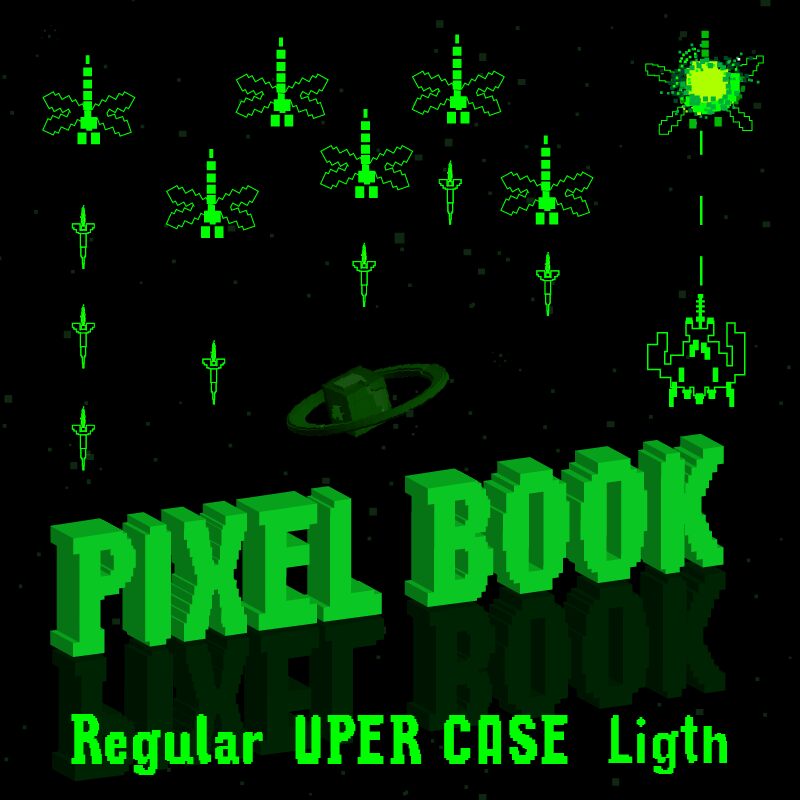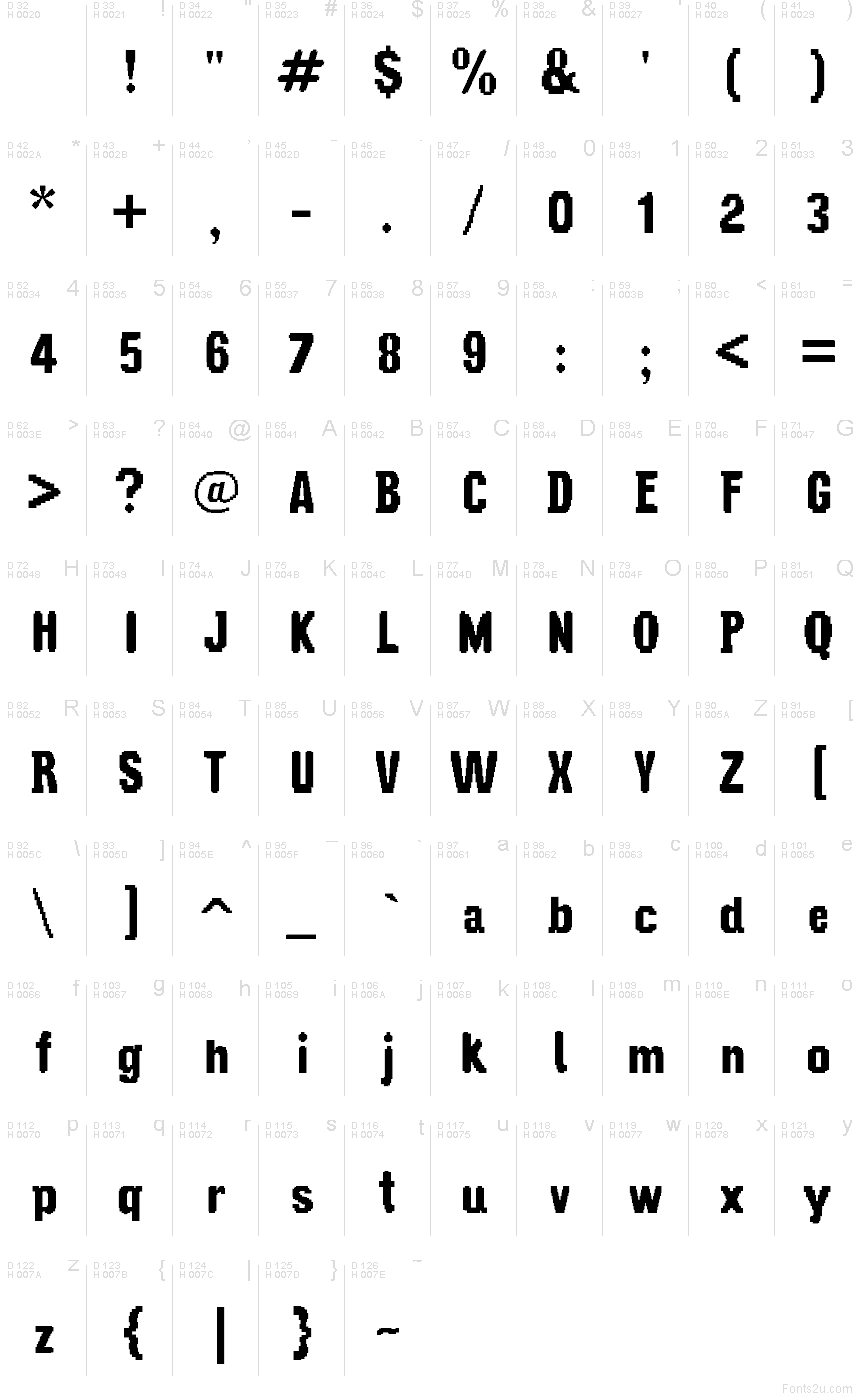
Pixel Book je bezplatný pixelový font od Galdino Otten. Písmena odkazují na ranou digitální typografii, vyznačují se blokovými hranami a pevnou, lehce starosvětskou siluetou. Kombinace ostrých čtvercových pixelů a povědomých tvarů připomínajících patkové písmo mu dodává retro digitální nádech, který působí spíše jako digitální pohádková knížka než jako výsledková tabule v arkádové hře.
Díky tomu je tento bezplatný font přirozenou volbou pro titulní obrazovky her, nadpisy plakátů, obálky časopisů, bannery aplikací a branding, který vyžaduje lehce retro vzhled v nízkém rozlišení. Dobře funguje i pro krátké citace a titulní karty, kde masivní pixelové tvary udržují hravý tón, zatímco klasické tvary písmen brání tomu, aby font působil příliš mechanicky.